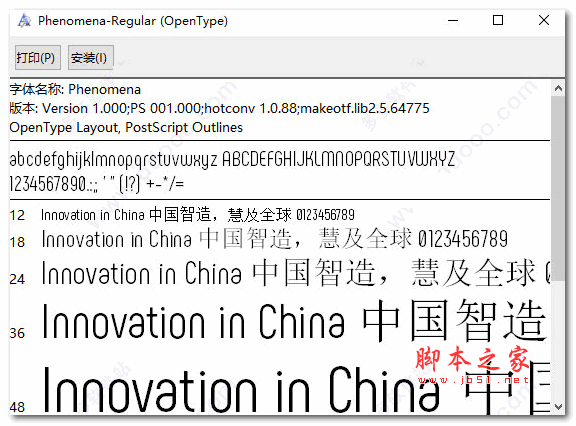
phenomena是一款適用性很廣泛的中文字體,該字體線條粗細(xì)適中,能夠?yàn)橛脩舫尸F(xiàn)一致的視覺美感,包括線條粗細(xì)不一的7款字體,分別為Phenomena-Black、Phenomena-Bold、Phenomena-ExtraLight、Phenomena-Regular、Phenomena-Thin,可以應(yīng)用于文本裝潢、信息展示、網(wǎng)頁設(shè)計(jì)、篆刻制模、數(shù)據(jù)制作、裝潢設(shè)計(jì)、計(jì)算藝術(shù)設(shè)計(jì)、視覺設(shè)計(jì)、字帖等一切合法應(yīng)用場(chǎng)景,有喜歡的朋友可免費(fèi)下載收藏。